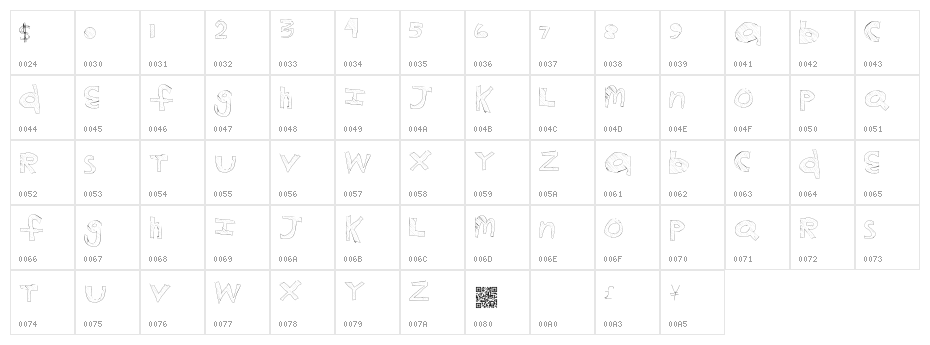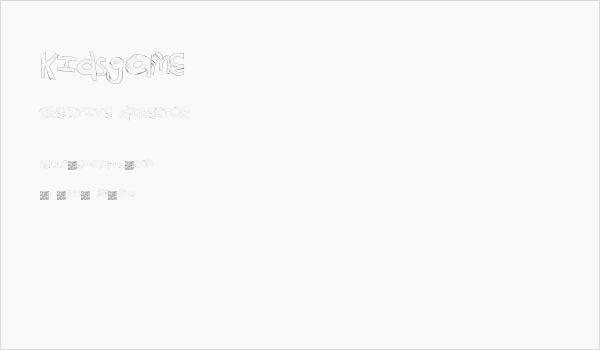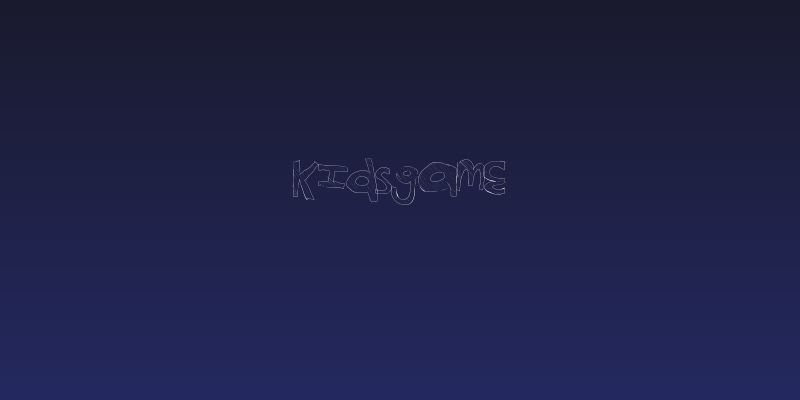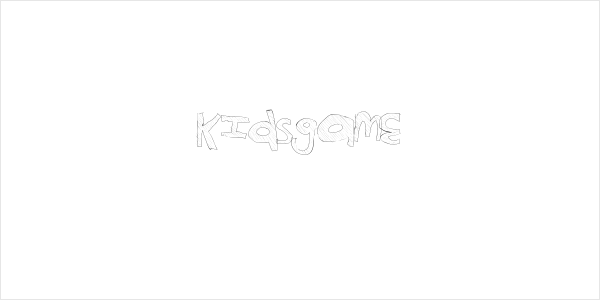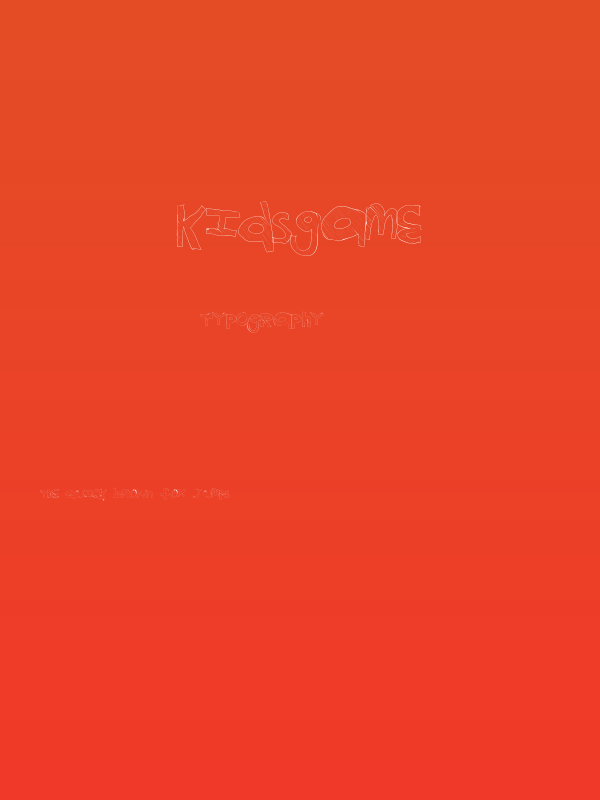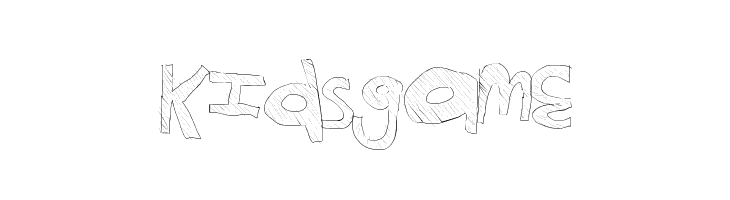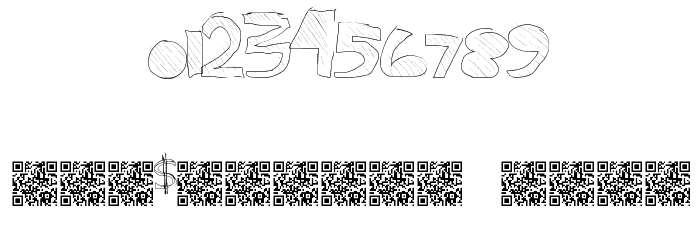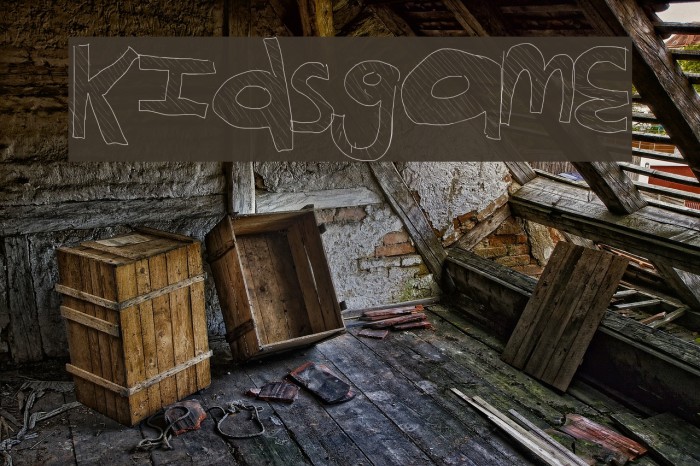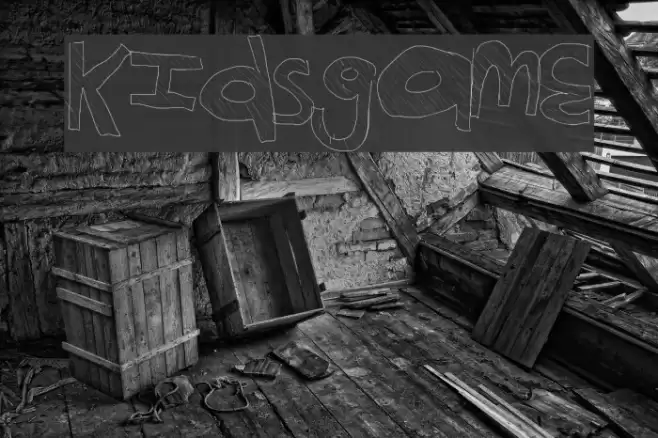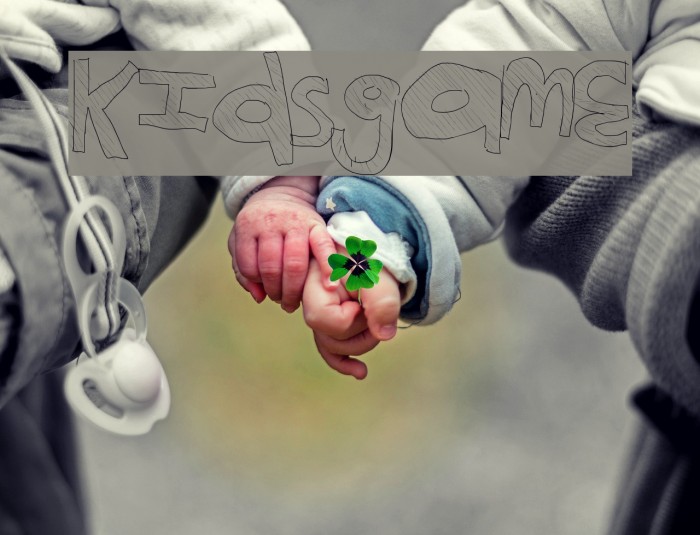
KidsGame Font
| Style général | Playful |
| Projets proposés | Ideal for children's books, educational materials, playful branding, and creative posters. |